Tìm hiểu font Việt hoá là gì? Khám phá top font chữ tiếng Việt đẹp cho thiết kế
Font chữ là yếu tố quan trọng trong mỗi bản thiết kế. Việc lựa chọn một font chữ đẹp và phù hợp không hề dễ dàng. FPT Shop sẽ giới thiệu đến bạn một số font chữ tiếng Việt đẹp cho thiết kế, giúp bạn có thêm nhiều sự lựa chọn hơn trong quá trình tạo nên tác phẩm nghệ thuật của mình.
Thế nào là font Việt hoá?
Không phải mọi font chữ đều dùng cho tiếng Việt được. Hiện nay trên thế giới có rất nhiều font chữ khác nhau từ nhiều quốc gia và nó chỉ hỗ trợ cho ngôn ngữ của quốc gia đó. Nếu muốn sử dụng font chữ này cho tiếng Việt thì cần phải Việt hoá. Có thể hiểu rằng font chữ Việt hoá là font chữ được chuyển đổi từ font chữ nước ngoài sang tiếng Việt.
Top các font chữ tiếng Việt đẹp cho thiết kế
Font Lato
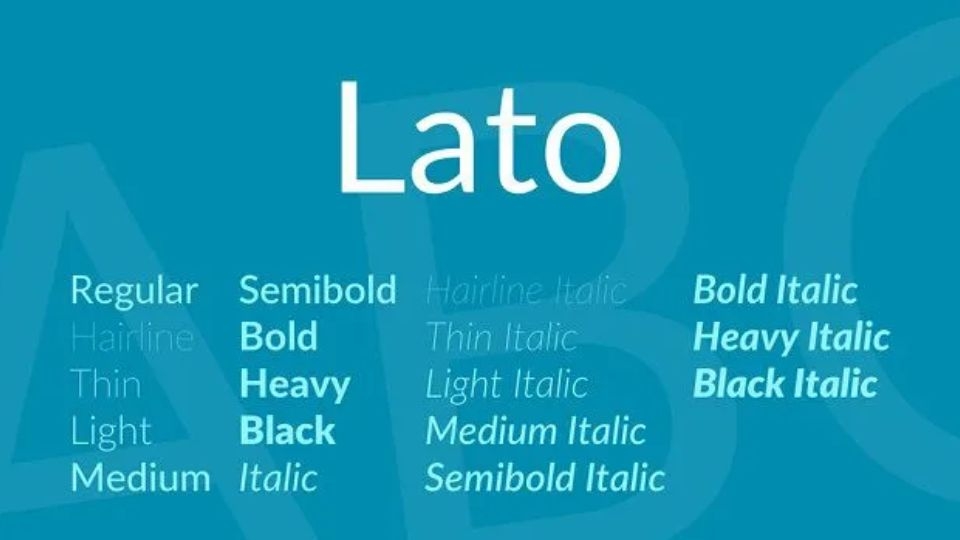
Lato (có nghĩa là mùa hè trong tiếng Ba Lan) là font chữ thuộc họ Sans serif, được thiết kế vào mùa hè năm 2010 bởi Lukasz Dziedzic. Sau đó, Google đã hỗ trợ xuất bản font chữ này theo Giấy phép Phông chữ Mở.
Font chữ Lato có các đường nét tròn nhẹ trên chữ cái, đem lại cảm giác ấm áp của mùa hè, bên cạnh đó nó cũng sang trọng nhờ thiết kế cổ điển.
Font iCielBC Downtown
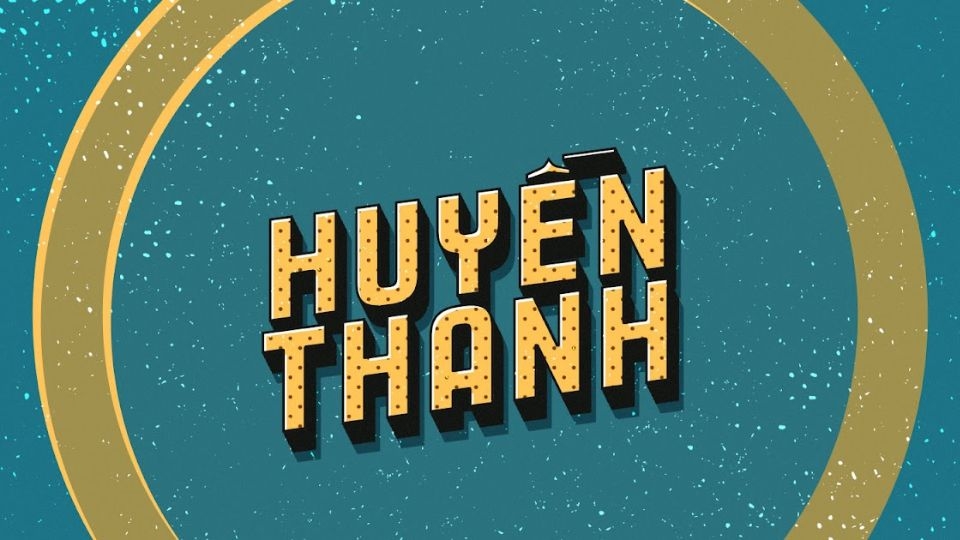
Font chữ này được một bạn nữ người Hà Nội thiết kế, được lấy cảm hứng từ các bảng hiệu vẽ tay, hình ảnh bình dị và màu sắc đơn giản từ thời bao cấp.
Font SVN-Product Sans
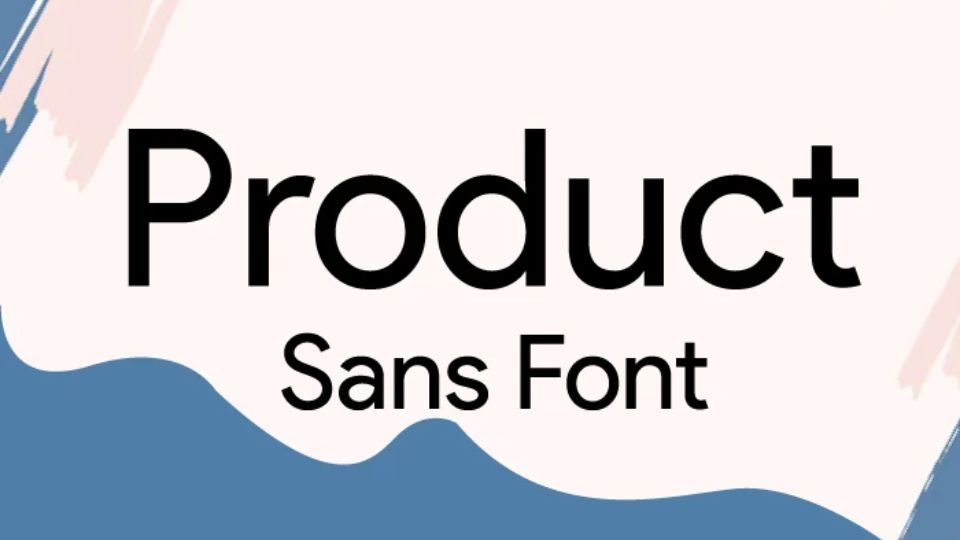
Font chữ SVN-Product Sans được Google thiết kế nhằm mục đích xây dựng thương hiệu cho riêng mình, dùng để thay thế logo Google vào tháng 09/2015. Khi tiếp xúc với các ứng dụng của Google, bạn sẽ dễ bắt gặp font chữ này.
Font Futura
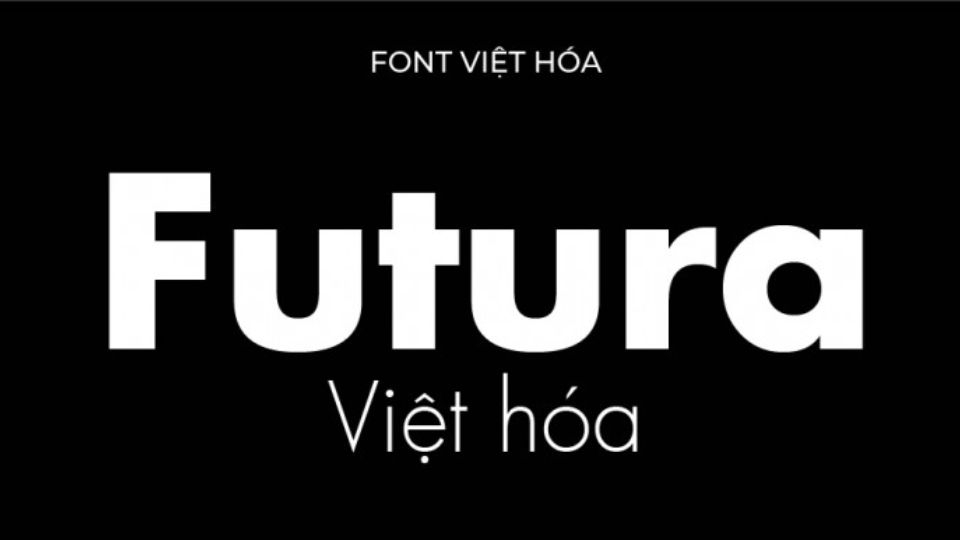
Futura là một trong những font chữ tiếng Việt đẹp cho thiết kế mà bạn không nên bỏ qua. Paul Renner là người thiết kế font chữ này dựa trên những hình dạng hình học, giống với tinh thần của phong cách Bauhaus thời kỳ đó. Dù font chữ Futura đã được ra đời từ lâu nhưng đến nay nó vẫn được nhiều người tìm kiếm.
Font Bìa Sách Xưa
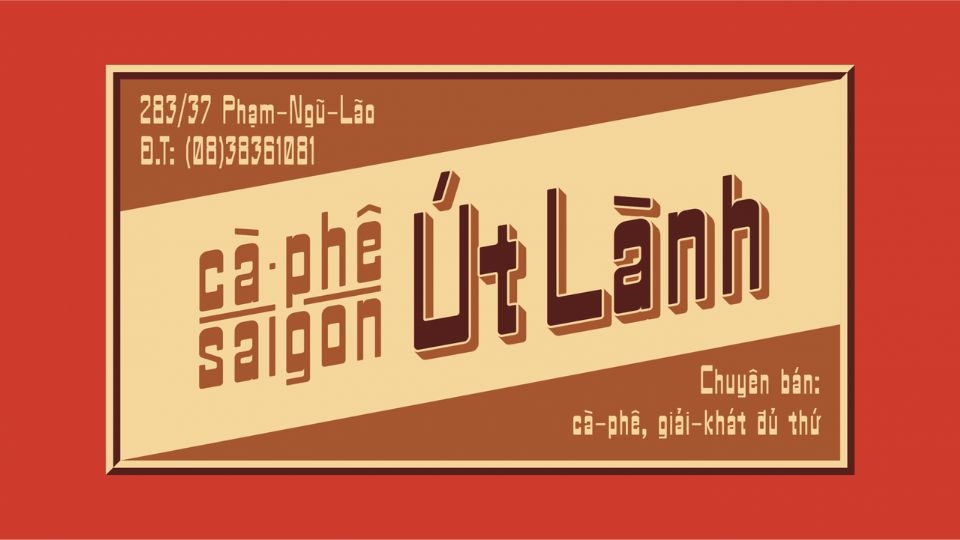
Font Bìa Sách Xưa được thiết kế bởi Tống Văn Diệp. Ông đã lấy cảm hứng từ các bìa sách cũ và biển quảng cáo của Việt Nam vào những năm 1980. Font chữ này có đường nét thẳng dọc mảnh khảnh và đường nét ngang dày, đem lại sự hoài cổ, hoài niệm cho người xem.
Font Bon Foyage
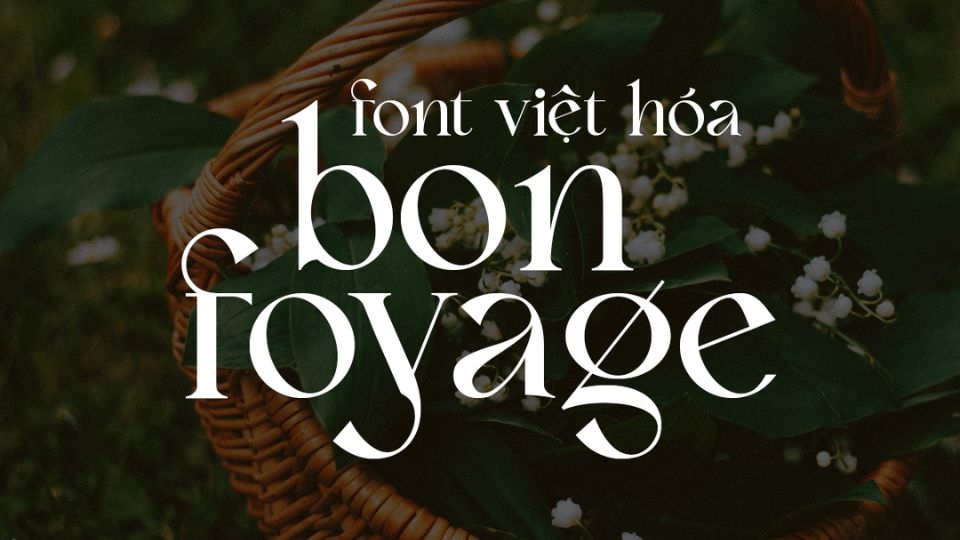
Font chữ này thuộc họ serif thư pháp mang phong cách hiện đại, thích hợp để dùng cho các chủ đề thiết kế như logo, thời trang, thương hiệu, tạp chí, lời mời, trích dẫn, nhiếp ảnh, áp phích, bưu thiếp, quảng cáo, tiêu đề blog, trang web, sách,...
Font SVN-TheUntold Story
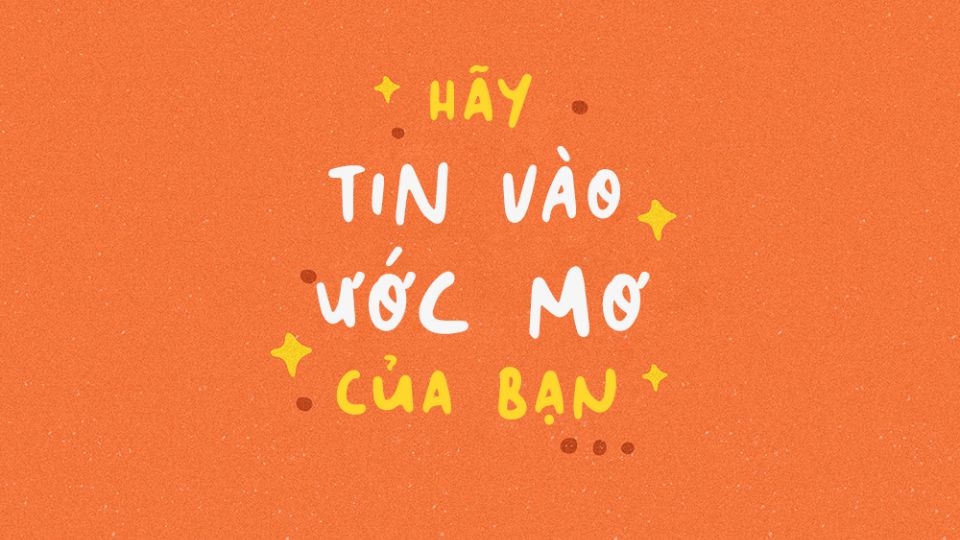
Font chữ này là kiểu viết tay theo phong cách tinh nghịch và vui nhộn, phù hợp cho các ấn phẩm thiết kế như bao bì sản phẩm, bìa album, bìa sách, thiệp chúc mừng, tờ rơi, thiết kế hình ảnh trong may mặc,...
Tạm kết